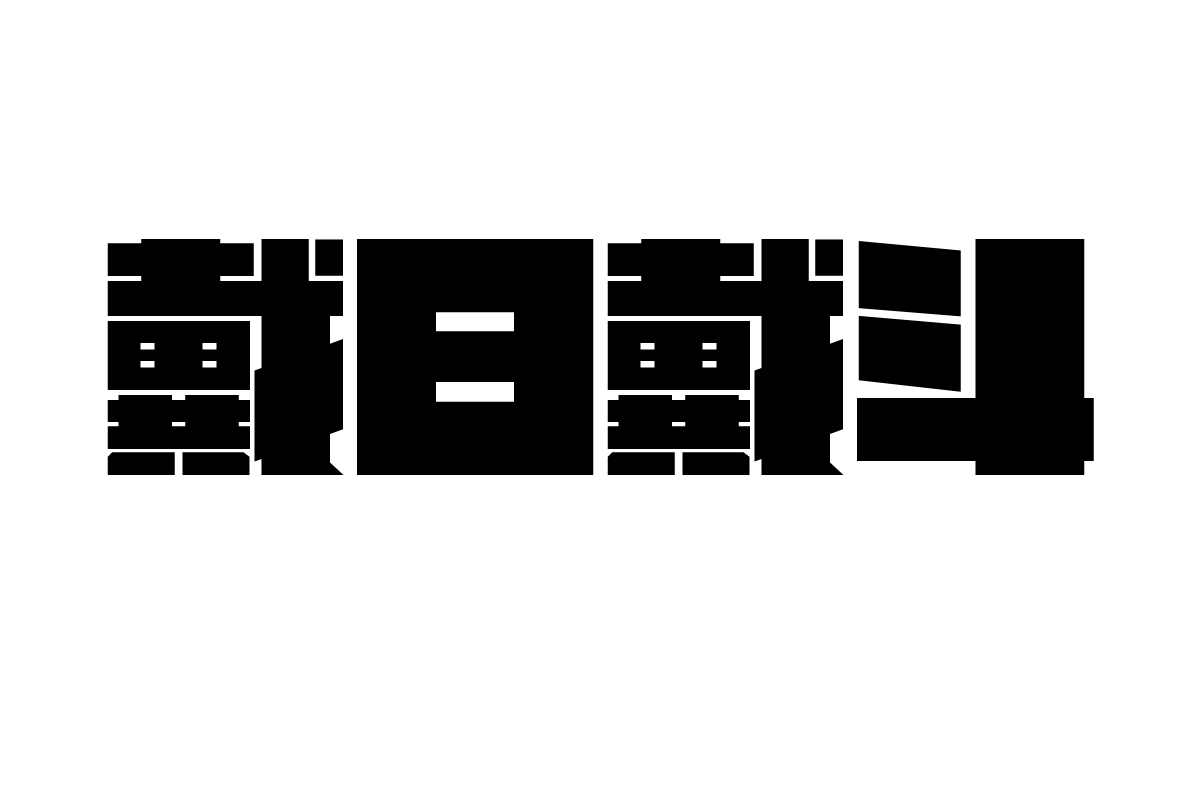
造字工房劲黑体是一款具有现代感和科技感的无衬线字体,适用于各种品牌标识、广告设计、网页设计等领域。这款字体的特点是笔画简洁有力,字形流畅自然,易于阅读和识别。它的设计风格独特,线条粗犷有力,给人一种强烈的视觉冲击力。此外,造字工房劲黑体的可读性也非常出色,无论是在哪种尺寸下,都能保持清晰易读的效果。